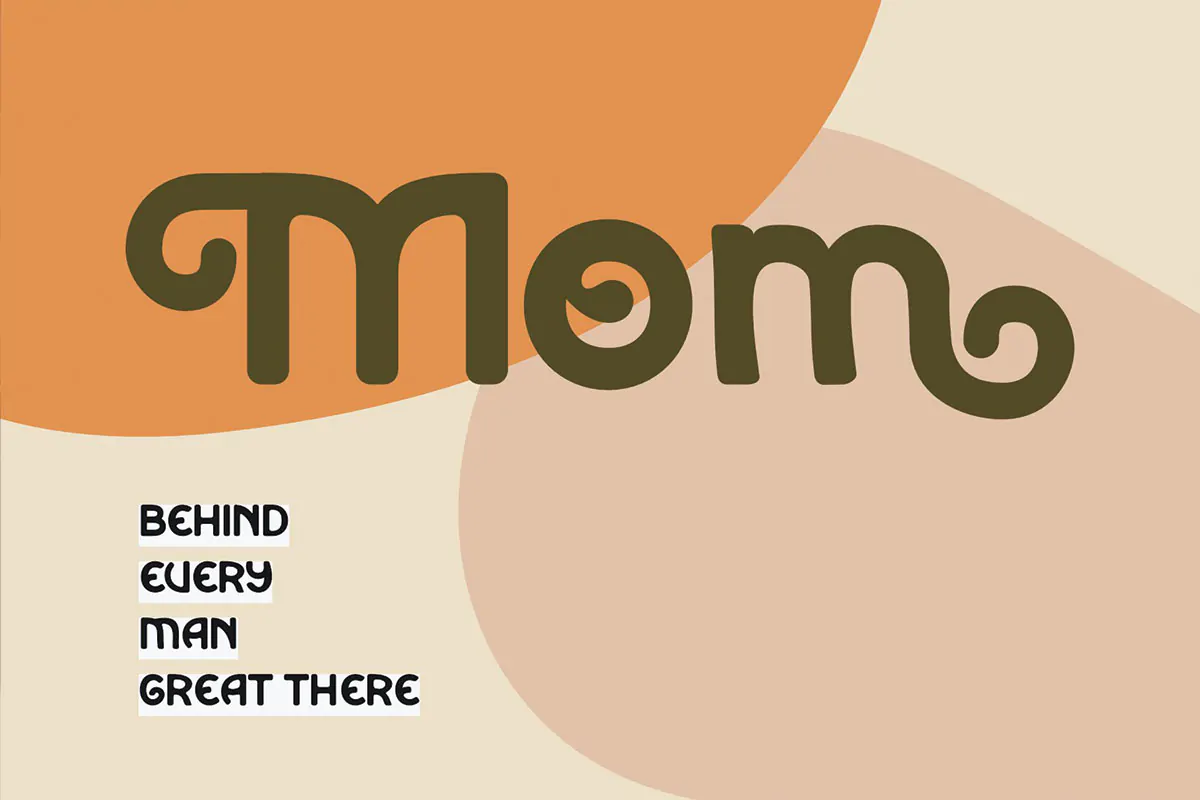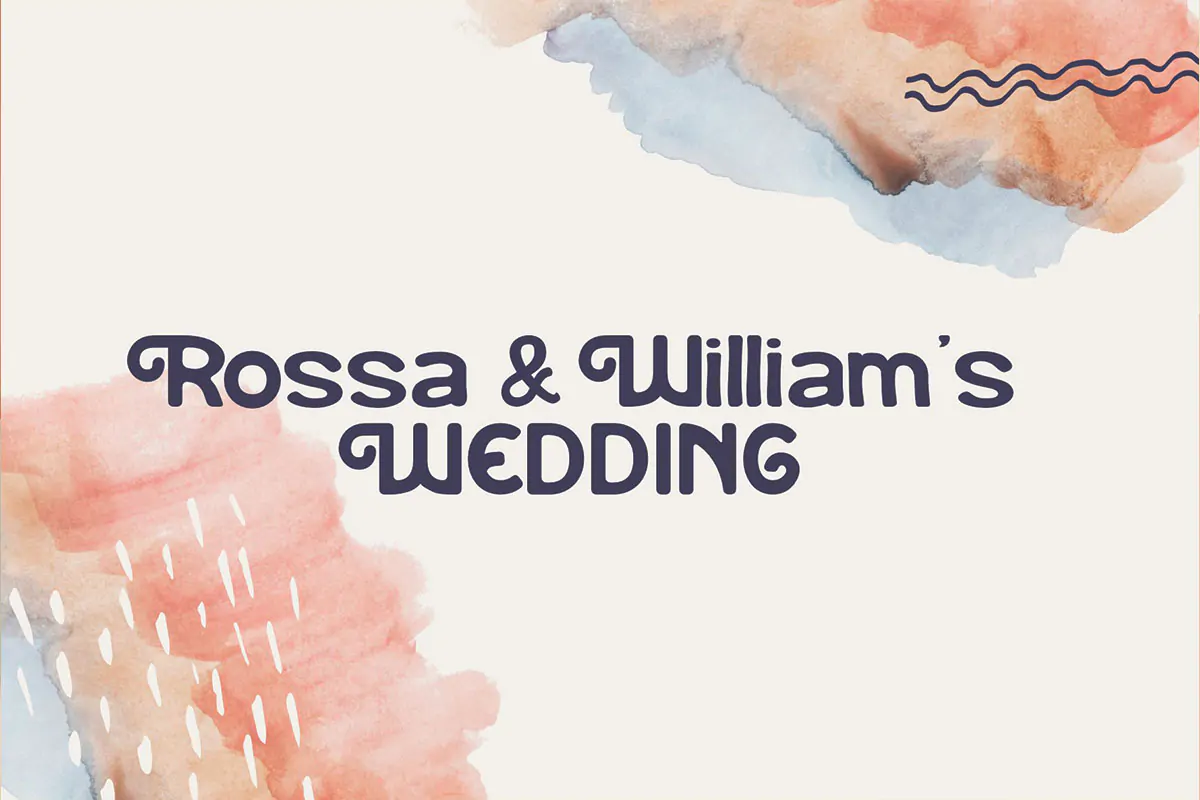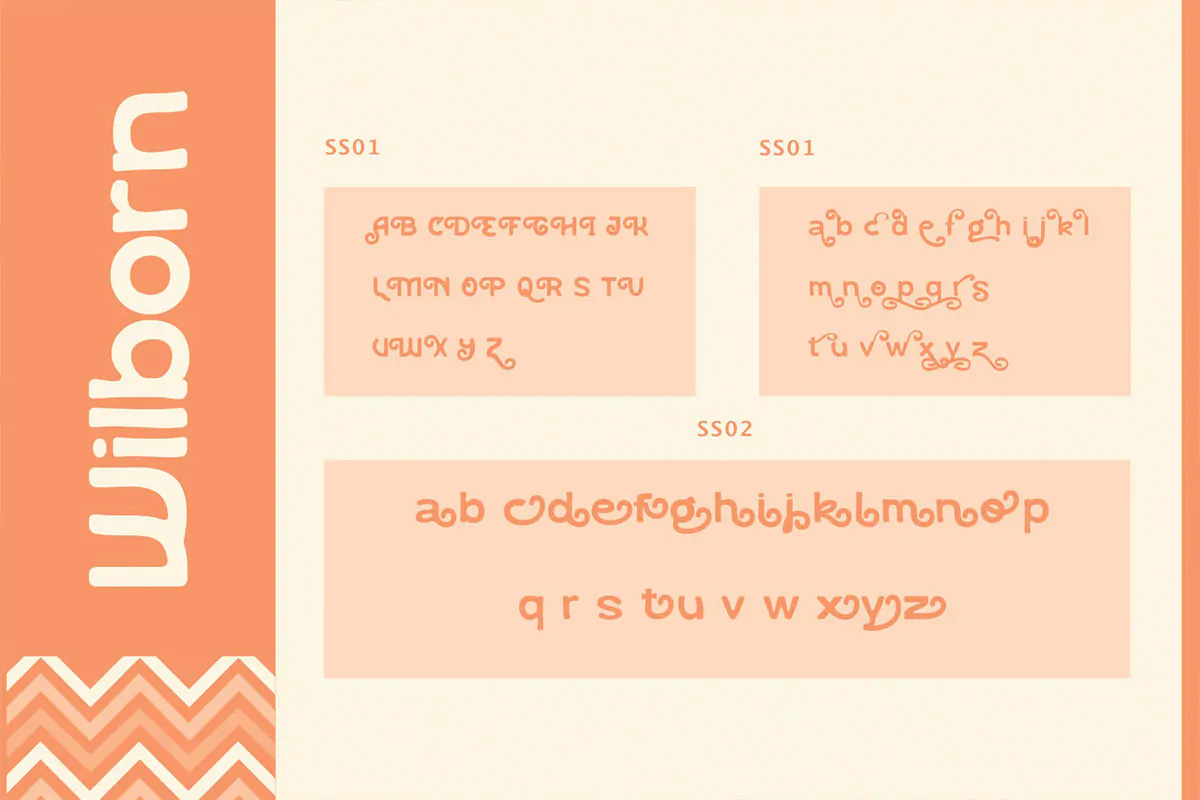
فونت فانتزی جالب کودکانه Wilborn
فونت فانتزی جالب کودکانه
فونت فانتزی جالب کودکانه Wilborn یک قلم نمایشی انگلیسی است که مناسب جهت استفاده در طرح و پروژههای گرافیکی مختلف به خصوص طرحهای کارتونی و کودکانه میباشد. فونت Wilborn با وزن معمولی طراحی شده است که میتوانید از آن در طراحی کارت تبریک، بسته بندی محصولات، ظروف یکبار مصرف، لوازم التحریر، لباس کودک و … استفاده کنید.